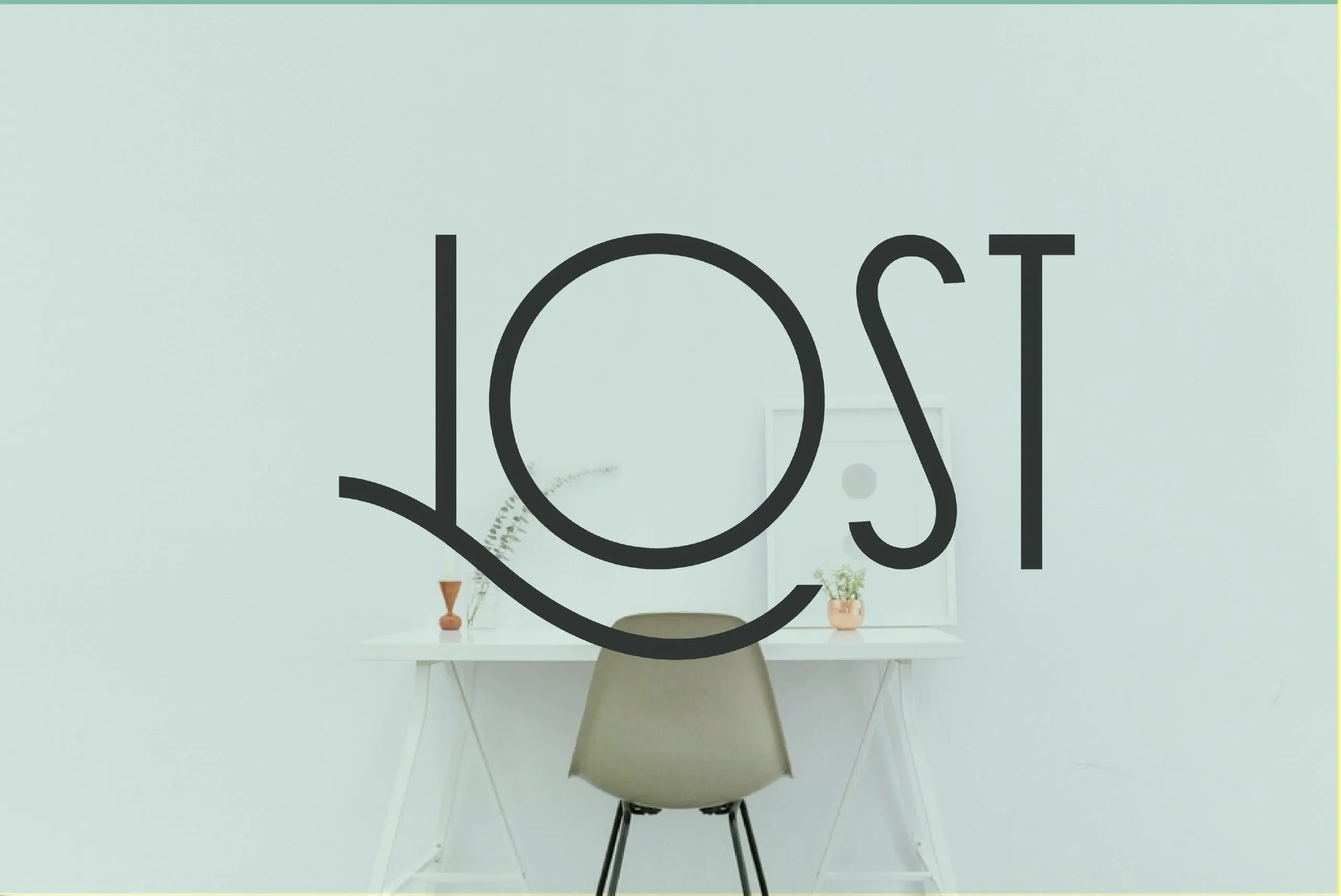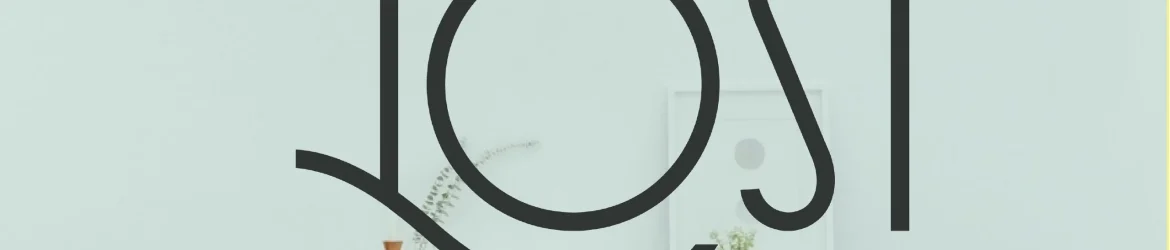
Introduzimos RedFlower Typeface! Desenvolvido pela Type & Studio, esta é uma fonte premium disponível na creativemarket. Aproveite agora e baixe essa fonte grátis para uso sem fins lucrativos. RedFlower Typeface apresenta um estilo moderno e minimalista, com traços leves e consistente. É perfeitamente adequada para criações como logomarcas, cartões de convite, cartazes, citações e cabeçalhos. Possui funções avançadas como swash, fracionamento e suporte multilinguagem, tornando-a uma opção versátil em diversas aplicações gráficas. Não perca essa excelente fonte que combina elegância com simplicidade.